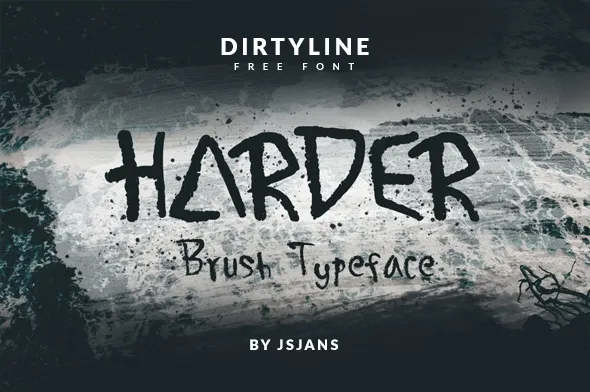
Harder Font – Fonte Grátis
Harder Font
Introduzimos Harder ! Harder – uma nova fonte tipo aquarela, projetada e compartilhada de graça pela Dirtyline Studio, uma casa de fontes profissionalizada no Creativemarket que oferece belas fontes para que você visite seu estabelecimento e adquira as suas. Harder é projetado à mão com uma aparência limpa e elegante, fácil mas cheia de arte. Esta fonte aquarela traz uma sensação natural e vibrante aos seus designs. É ideal para adicionar um toque artístico e original às suas criações digitais. Com sua beleza única e versátil, você pode usá-la em diversas aplicações do seu design – seja para criar gráficos de marketing, desenhos digitais, arte digital ou até mesmo como fontes base no seu próximo projeto. A Dirtyline Studio oferece não apenas uma fonte aquarela, mas uma ferramenta que pode transformar qualquer trabalho de design em algo único e cheio de personalidade. Experimente Harder ! Harder – sua nova font favorita para se divertir na criação!